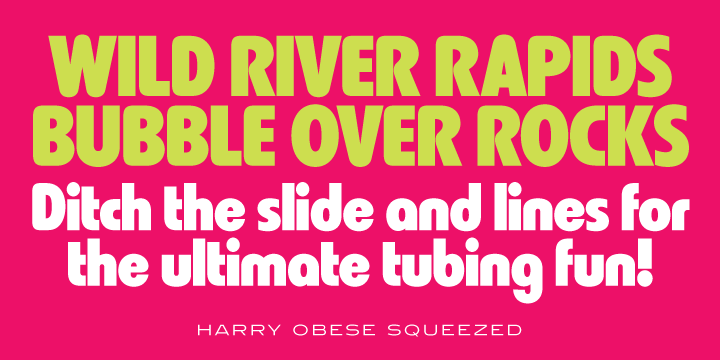
Harry Obese (Red Rooster)
Steve Jackaman und Ashley Muir von Red Rooster haben eine populäre Schrift der Vergangenheit ins digitale Zeitalter gerettet:
Harry Pro ist der digitale Nachfolger von Harry Obese (wovon es bislang nur unzureichende inoffizielle Digitalisierungen gegeben haben dürfte).
»This revival of Harry is based on the original design by Marty Goldstein (and C.B. Smith). Goldstein, born in Chicago in 1939, was the co-founder of the groundbreaking Creative Black Book. He graduated from the Pratt Institute in 1960. Harry, first published by VGC in 1966, was named for his father. ITF has added four new weights to the original six.«